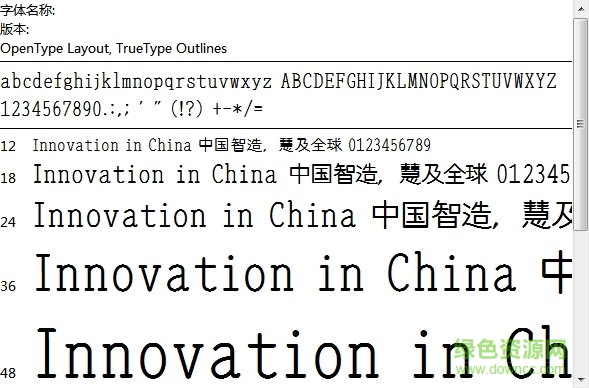
薄櫻體是一款適用于系統(tǒng)字體的端正字體,筆畫流暢、造型端方,有著容易辨認(rèn)的外觀和結(jié)構(gòu),讓大家的閱讀更加舒適和便捷,喜歡的朋友不妨來綠色資源網(wǎng)體驗(yàn)吧!
薄櫻字體一筆一畫非常端正,字形大方得體,整體效果非常出色,可廣泛應(yīng)用于平面設(shè)計、廣告設(shè)計、報紙雜志、正文標(biāo)題等領(lǐng)域。
薄櫻體可以運(yùn)用在電腦中來標(biāo)注嚴(yán)謹(jǐn)圖文,也可以當(dāng)做手機(jī)字體,讓系統(tǒng)文件更容易被讀取,同時也可以為你的平民設(shè)計、包裝設(shè)計帶來比較美觀的體驗(yàn)。